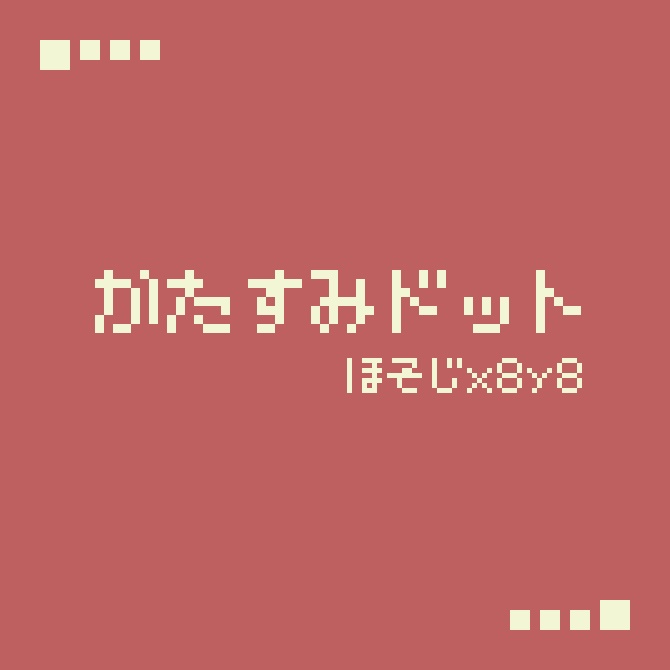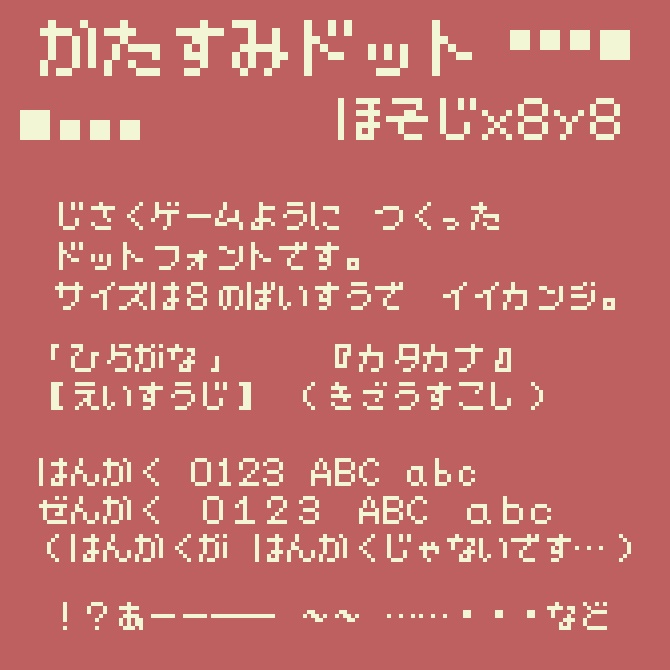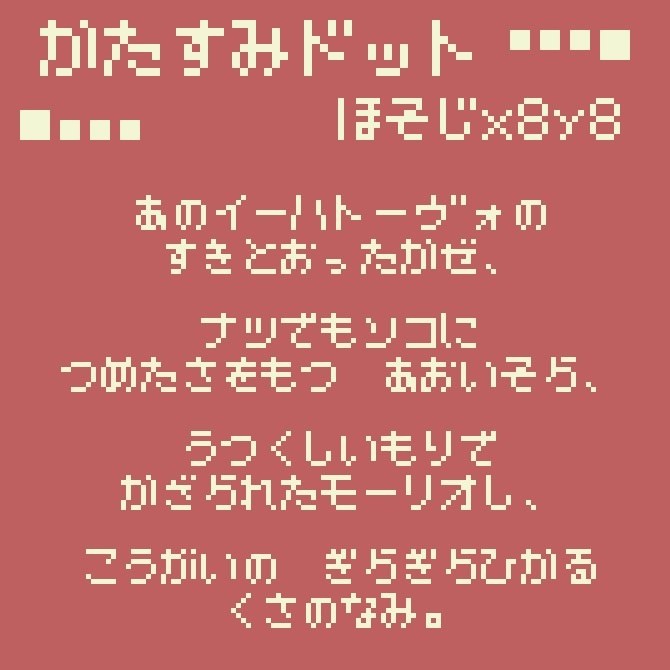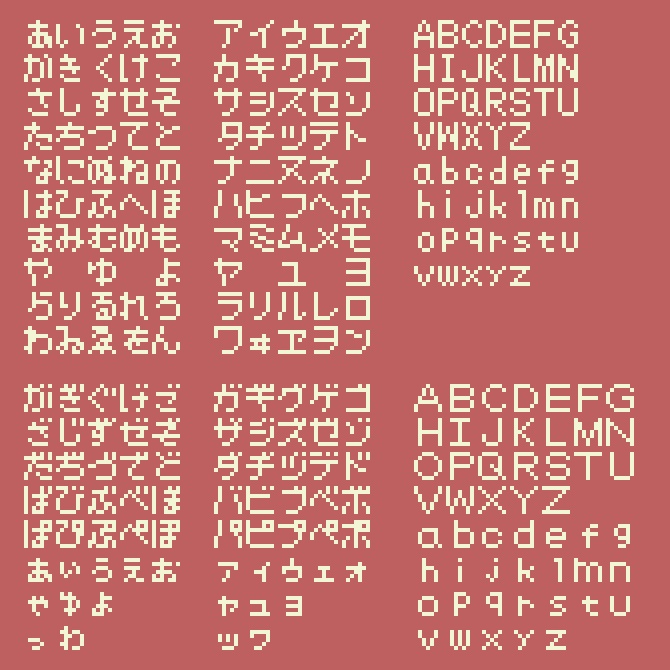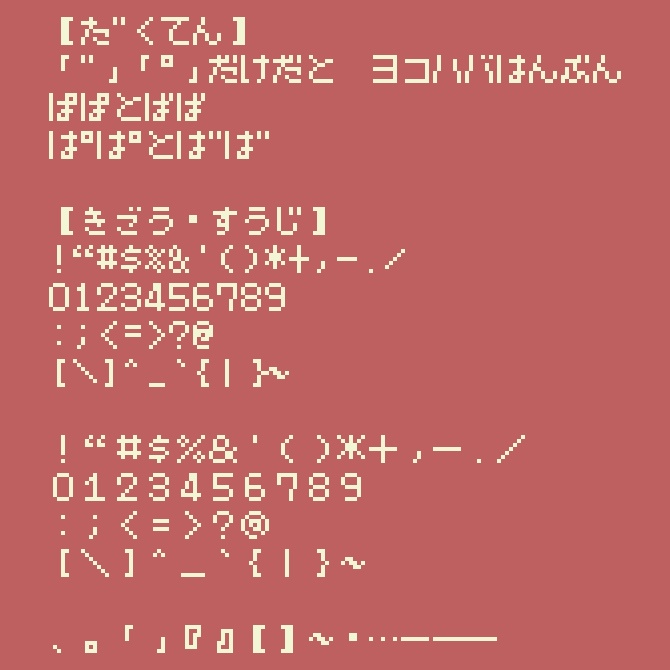
【フリーフォント】かたすみドット ほそじx8y8【商用利用可】
かたすみドット ほそじx8y8 KatasumiDotHosojix8y8 Version 202602 ------------------------------------------------------------ 概要 ------------------------------------------------------------ 本フォントはゲームへの埋め込みを想定したドットフォントです。 サイズを8の倍数にする事でピクセルパーフェクトに対応します。 ゲームを想定していますが、他の制作物や用途にも使用できます。 このフォントは、商用・非商用問わず自由にご利用いただけますが、 すべて無保証とします。 再配布可能。 制作物のコードやプロジェクトファイルの公開に同梱する等、 本フォントがそのまま見える状態でも問題ありません。 (加工・改造した際は下記の利用規約が条件) 小容量のフォントなので、データのかたすみに置いてやってください。 ------------------------------------------------------------ 利用規約 ------------------------------------------------------------ 本フォントは、商用・非商用を問わず無料でご利用いただけます。 クレジット表記の有無は問いません。 制作物の内容・表現方法を問わず利用可能です。 本フォントは加工・改造を自由に行えます。 ただし、 ・加工・改造したttfデータを主とした配布 ・加工・改造した素材データとして配布 いずれかの場合、本フォント「かたすみドット ほそじx8y8」または「KatasumiDotHosojix8y8」を 加工・改造した旨を、利用者が容易に確認できる箇所へ明記してください。 【ttfデータそのものを主とした配布の例】 ・フォント単体での配布 ・フォント集への収録 など 【容易に確認できる箇所の例】 ・readme ・配布ページ ・クレジット表記 など 本フォントの利用条件は、利用開始時点で公開されている最新版の利用規約に従うものとします。 本利用規約は、予告なく変更される場合があります。 ------------------------------------------------------------ 禁止事項 ------------------------------------------------------------ 本フォントを自作したと偽る行為。 (加工・改造した箇所の自作発言は可能です。) 本フォントの利用に関して、他利用者の利用を制限する行為。 (加工・改造した制作物についての制限は自由です。) ------------------------------------------------------------ 使用ソフト・ツール ------------------------------------------------------------ Aseprite ase2ttf FontForge ------------------------------------------------------------ その他 ------------------------------------------------------------ ご紹介いただける場合、作者の名前表記は「かぼちゃ大豆」又は「kabotyadaizu」でお願いします。 下記の連絡先とあわせてご案内いただけると嬉しいです。 例:かぼちゃ大豆(X:@kabotyadaizu000) 再配布は可能ですが ttfデータそのものを主とする場合、下記の連絡先のどれかが5年以内に更新されていたら そこから繋がるリンクからダウンロードする形にしていただけると嬉しいです。 お願いベース。してない人を見つけても報告不要です。 (報告されたらそれはそれで何で何で知りたい知りたいわくわくウッヒョーと覗き見に行くかもです) ------------------------------------------------------------ 連絡先等 ------------------------------------------------------------ X(旧Twitter):https://x.com/kabotyadaizu000 BOOTH:https://kabotyadaizu000.booth.pm/ ブログ:https://kabotyadaizu000.hatenablog.com/